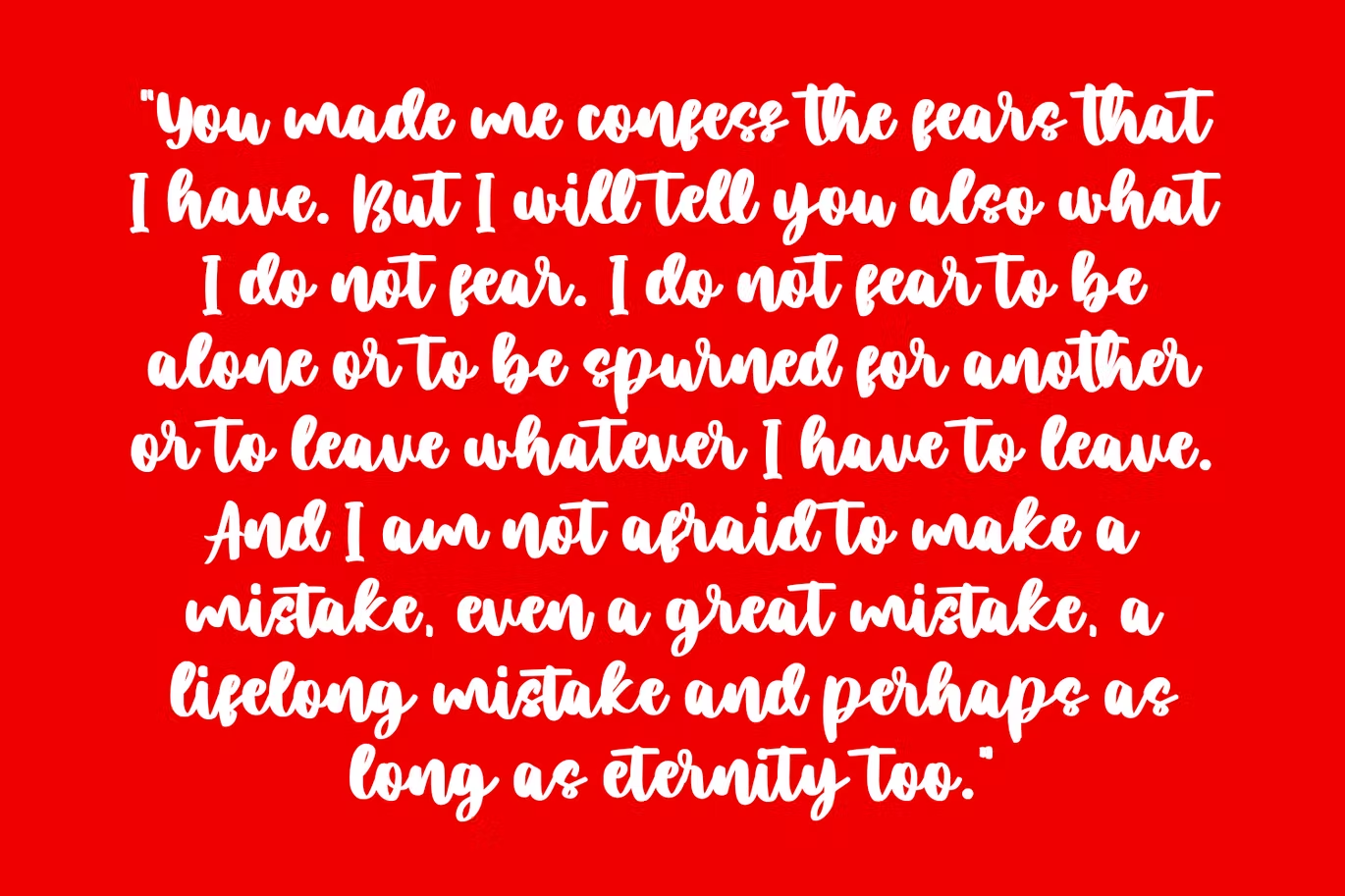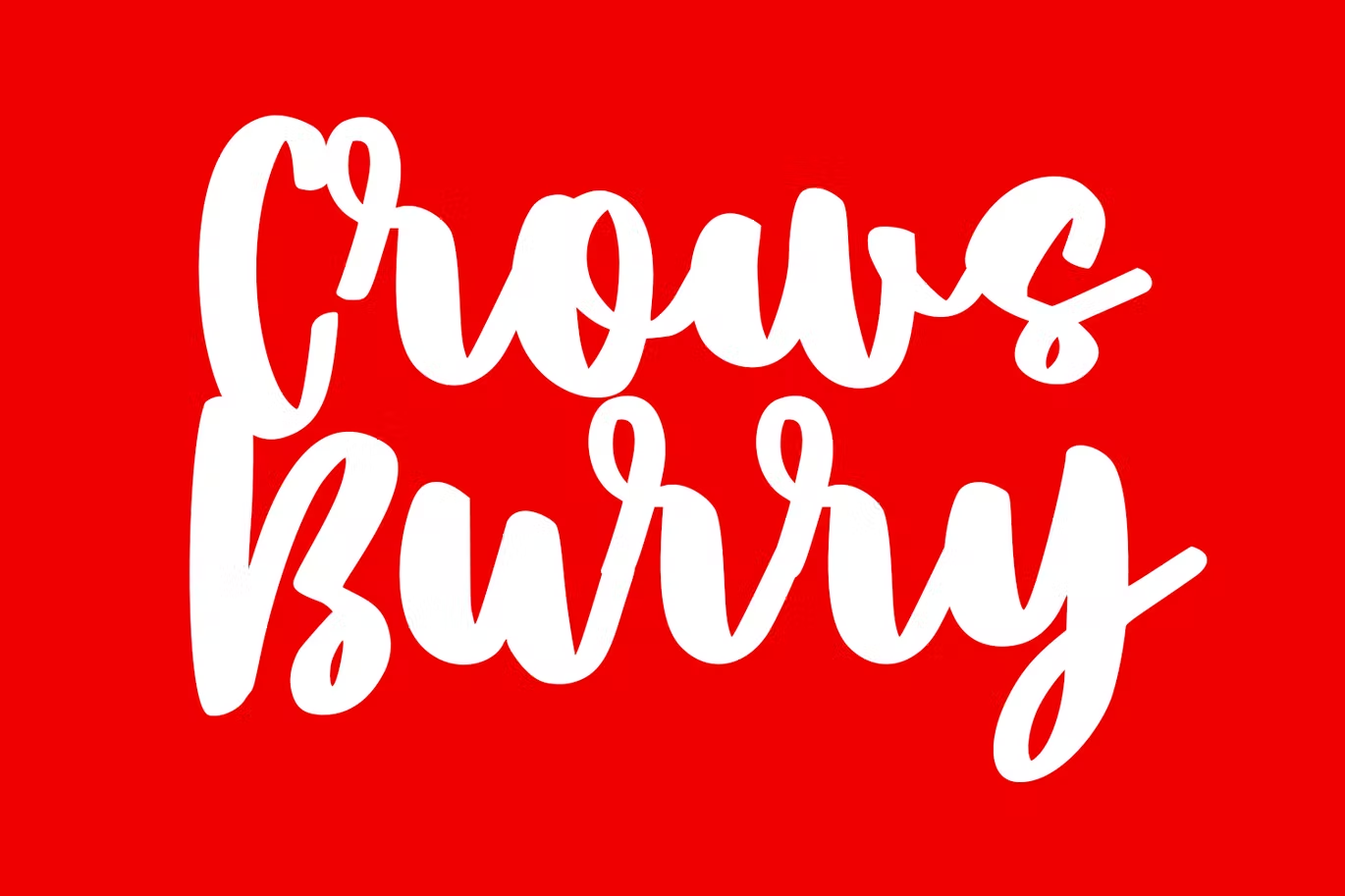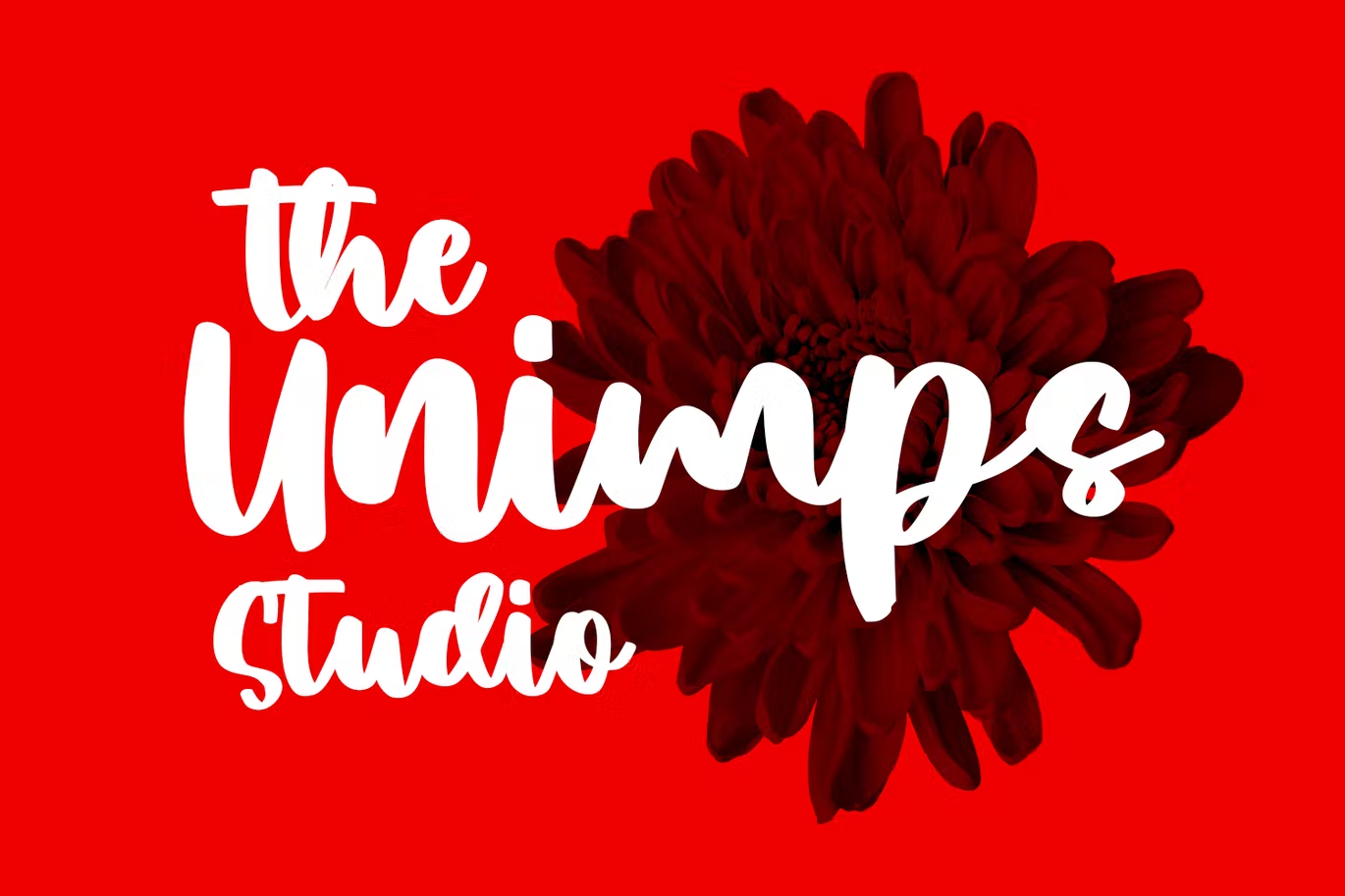
Bhonitta Script Font
Description de Bhonitta Script Font
Bhonitta est une police de script manuscrite sophistiquée. Avec un trait audacieux, un caractère amusant avec un peu de ligatures et d’alternatives. Pour vous offrir un travail créatif supplémentaire. La police Bhonitta prend en charge plus de 100 langues multilingues. Cette police convient à la création de logos, aux médias sociaux, aux titres de films, aux titres de livres, à un texte court, voire à une longue lettre de texte, et convient à votre police de texte secondaire avec sans ou empattement. Réalisez un travail époustouflant avec la police Bhonitta.